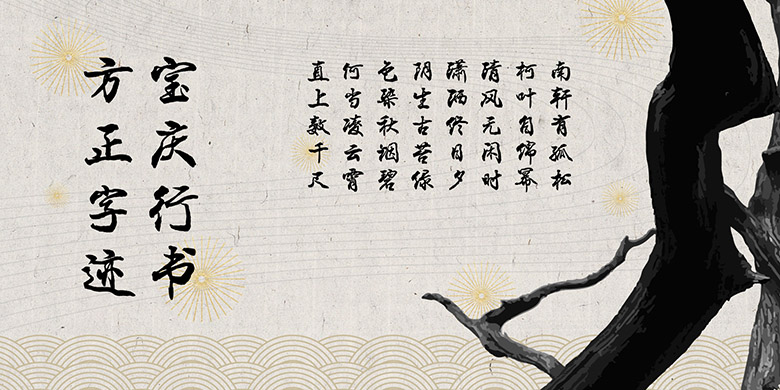
方正字迹-宝庆行书
郭宝庆,2008年为北京奥运会官方宣传品书写《北京》及《北京欢迎你》。作品被奥组委,联合国及相关首脑和机构收藏。2014年为中国APEC峰会题写国礼礼单欢迎词赠二十一国元首。
方正字迹-宝庆行书,做为电脑字库,作者在创作时力求行书端庄平稳,中正安舒,字体易于识别、字型规范而不失特色。行书的运笔加入了一些魏碑的抑扬顿挫。